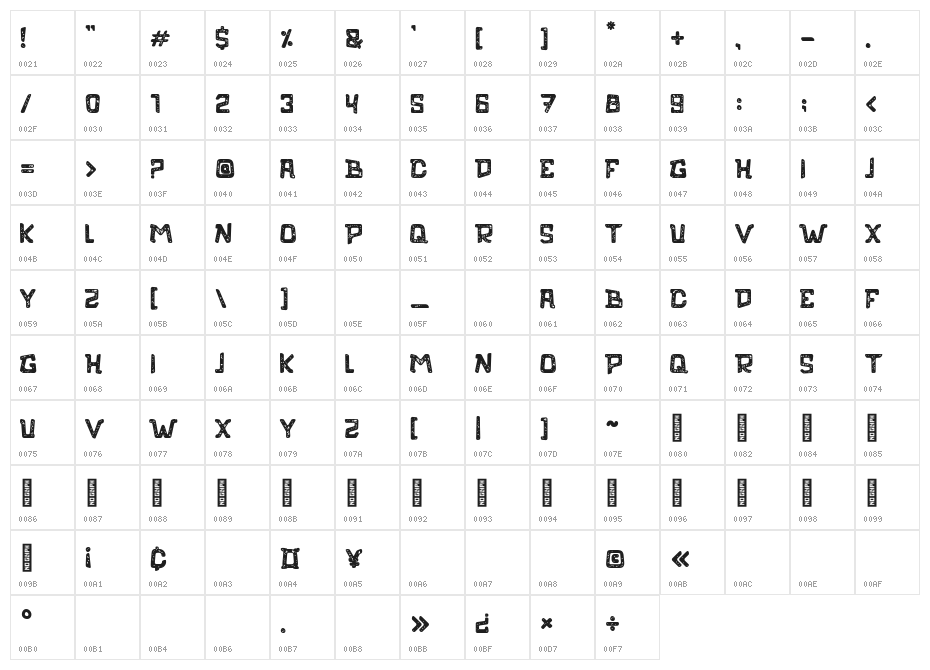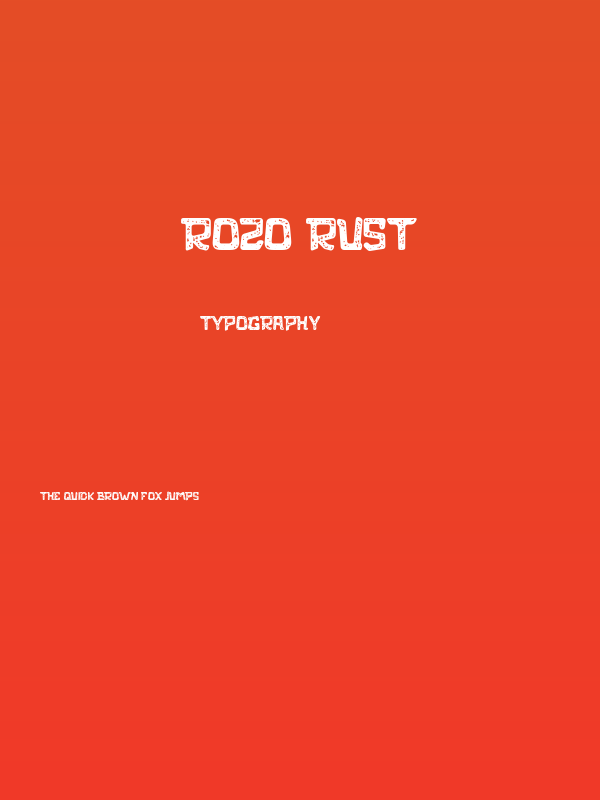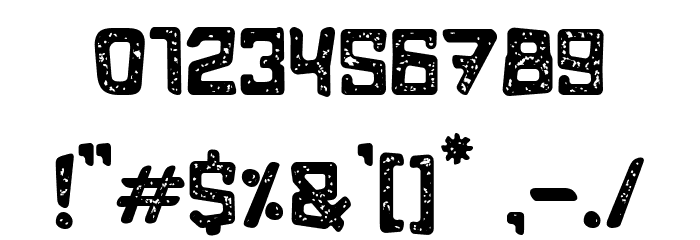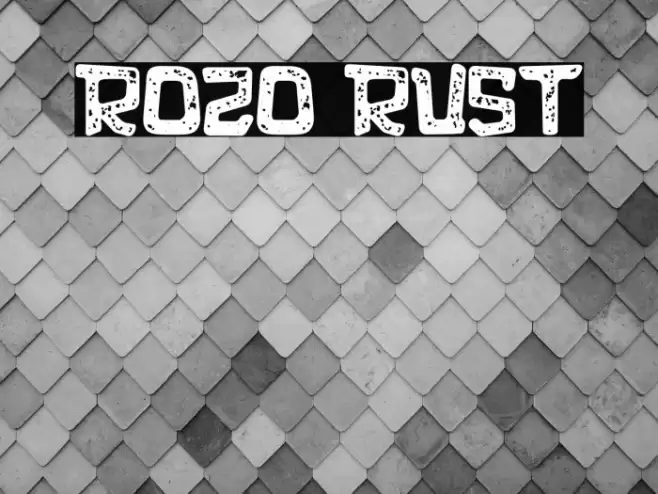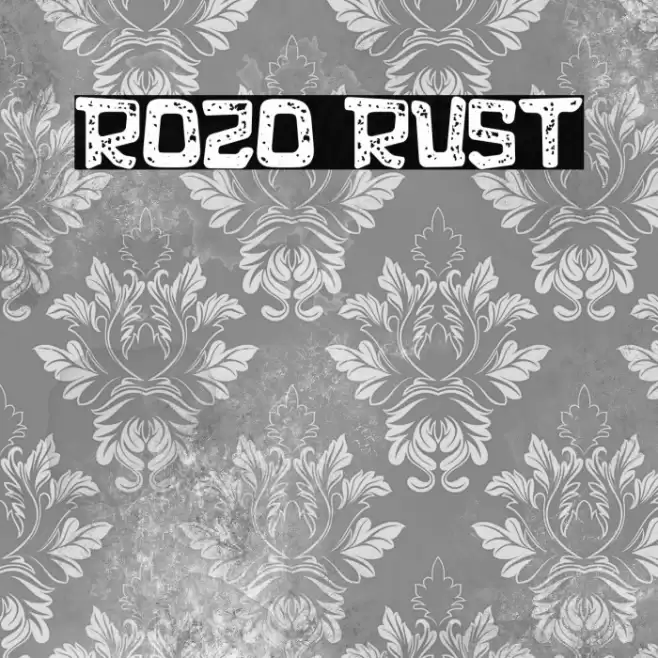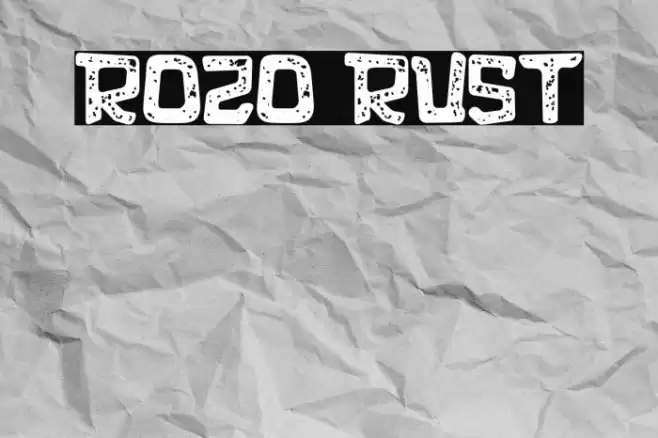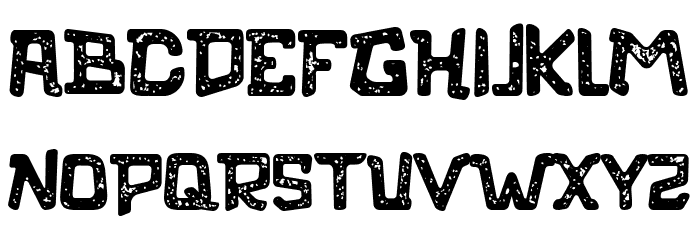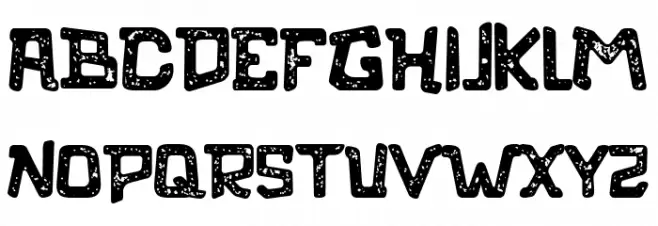
rozo Rust Font
✎ Messy
| النمط العام | Vintage |
| مشاريع مقترحة | Ideal for posters, album covers, branding for edgy or rustic products, and any design needing a bold, textured look. |